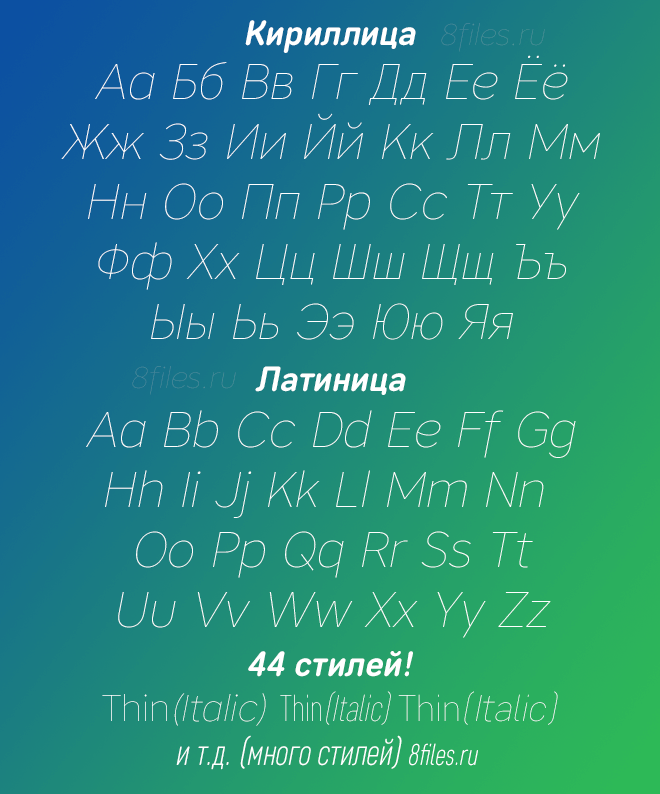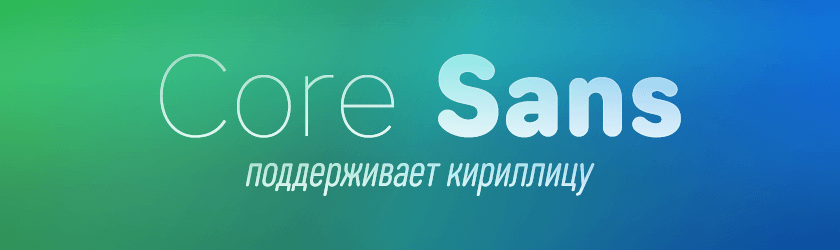
Font (шрифт) Core Sans
Привет всем. Представляю вашему вниманию современный шрифт (font) Core Sans. Он прекрасно подойдёт для дизайнерских целей, так как в него входит аж 44 стилей и ещё поддерживает Кириллицу! Скачай его себе совершенно бесплатно и пользуйся на здоровье